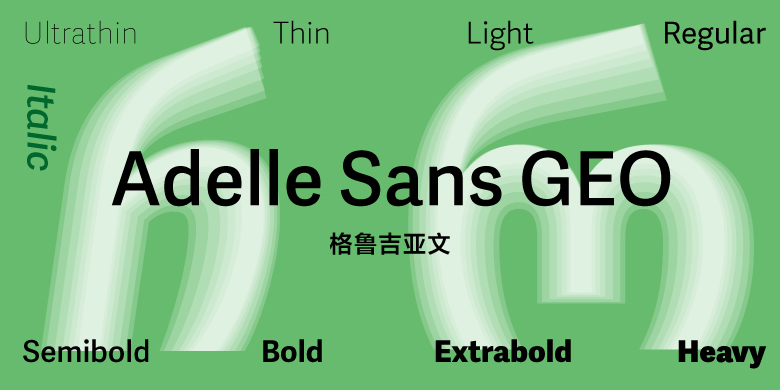
Adelle Sans GEO
Razmadze,Akaki
无衬线体
可用于格鲁吉亚文字的字体系列不多,尤其设计师和用户都喜爱的传统怪诞体。Adelle Sans的格鲁吉亚文字与原有的拉丁文字风格自然和谐。将已有的特点以及自然的形态结合起来,用于其他字体是相当具有挑战性的。格鲁吉亚字符在Adelle Sans中拥有所有这些和谐的感觉,我相信格鲁吉亚的用户会喜欢使用这款字体。